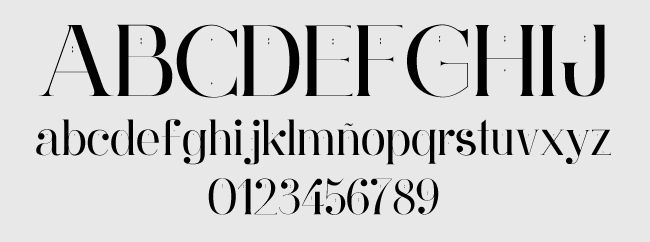
Esta tipografía gratuita recuerda, sobre todo por la limpieza de sus trazos, a Bodoni o Didot. Como elemento diferenciador, dichos trazos son un poco más gruesos, pero cada caracter, tanto en caja baja como en caja alta posee unos minúsculos puntitos que le aportan mucha personalidad. Es por eso una tipografía perfecta para branding o creación de logotipos.
This free typography remembers, mainly by the cleanness of its strokes, to Bodoni or Didot. As a differentiating element, these strokes are a little thicker, but each character, both in lowercase and in uppercase, has small dots that give it a lot of personality. That’s why it is a perfect typography to use on branding or to create logos.